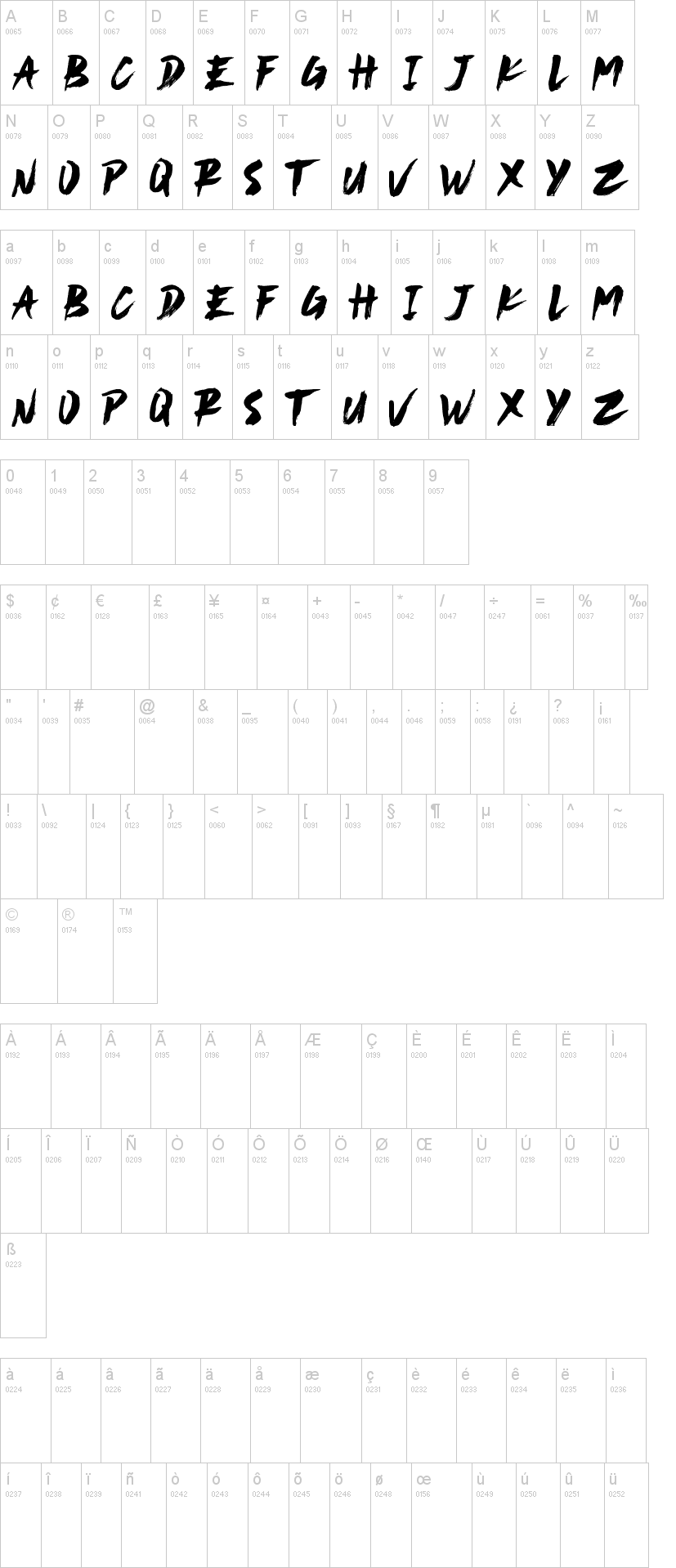
Never Settle
Never Settle 是一种字体,它是由 OnePlus 公司设计的,旨在为其品牌形象和产品推广提供独特的视觉效果。该字体是 OnePlus 的品牌标志,广泛应用于其宣传材料、广告、产品包装和其他营销材料中。它的设计灵感来自于 OnePlus 品牌的理念“不断追求卓越”,具有现代、简洁和大胆的视觉特点。该字体的线条流畅,字母间距离适中,易于阅读和识别。Never Settle 字体提供各种字重和字形,包括正常、粗体、斜体和粗斜体,以满足不同情境下的需求。
Never Settle是一款非常不错的手写艺术字体,具有很好的视觉感,适合于文化类的宣传设计、商业类品牌的广告和产品包装设计以及个性化文字排版等较多场景。